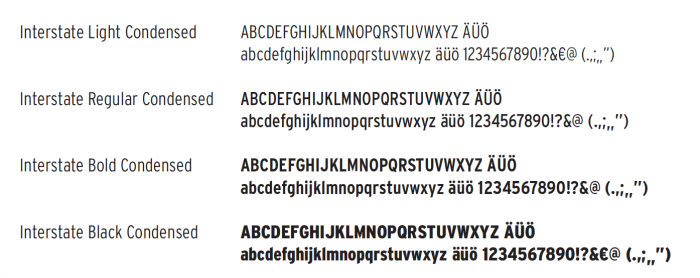
Interstate Ersatz für Word-Briefvorlage?
mein Kunde möchte unbedingt eine Ersatzschrift für die Interstate Light Condensed und die Interstate Bold Condensed. Er möchte eine Word Briefbogen Vorlage erstellen, die auf "allen" möglichen Rechnern funktioniert. Mir stehen die Haare zu Berge!
Nun möchte er von mir wissen welche Schrift am Ähnlichsten ist und sozusagen automatisch mit Word ausgeliefert wird. Meinen Vorschlag einfach eine ganz andere Art zu benutzen, z.B. Times, wurde abgelehnt. Lange Diskussionen ohne Ergebnisse. Ich weiß nicht mehr weiter. Habt ihr eine Idee oder einen Vorschlag wie das Problem zu lösen ist? Wäre euch sehr dankbar.
Wenn es plattformunabhängig und abwärtskompatibel sein soll, dann läuft es höchstwahrscheinlich auf Arial Narrow hinaus.
Da die Vorlage die schmale Interstate ist und man hier auf Nummer sicher gehen sollte, würde ich auch zur Arial Narrow raten. Wenn auch mit einer Träne in den Augen.  :roll: